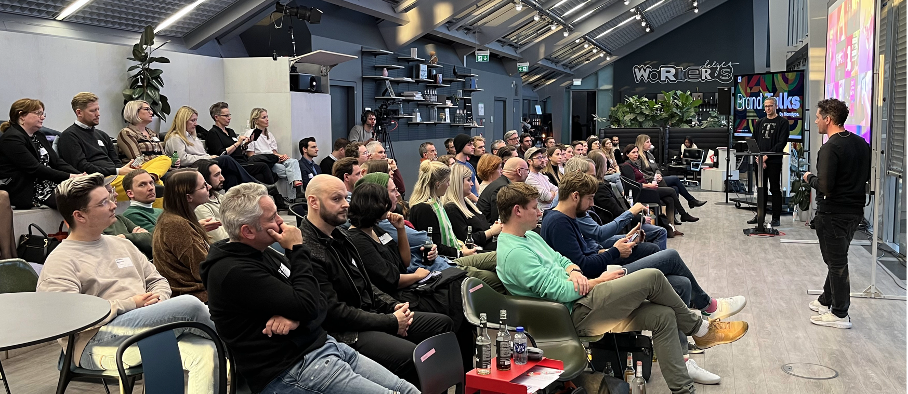
Brand Talks München verpasst?
Nach zweieinhalb Jahren Pause fanden Mitte November in München die 31. Brand Talks statt, veranstaltet von Monotype. Die wirtschaftlichen Vorzeichen haben sich in diesem Zeitraum extrem verändert. Auf den Corona-Lockdown folgten mehrere Infektionswellen, unterbrochene Lieferketten, die Energiekrise, Inflation und zuletzt Kurseinbrüche an der Börsen und bei den Kryptowährungen. Die Weltwirtschaft im Dauerkrisenmodus. Wie kommen wir da wieder raus? Rund 100 Besucher:innen bekamen Antworten auf diese Frage.
Wenn die Umsätze zurückgehen, sparen Unternehmen zuerst bei den Dingen, die sich schnell zusammenstreichen lassen: Werbung und Marketing. Genau das ist falsch, sagen die Markenprofis, denn Sparmaßnahmen in diesem Bereich sind oft der Beginn einer Abwärtsspirale. Sie betonen, dass es gerade in schlechten Zeiten von Vorteil sei, vertrauensvoll mit den Verbrauchern zu kommunizieren. Diese Ansicht vertritt auch der Brand-Talks-Eröffnungssprecher Simon Betsch, Managing Partner bei der Markenberatung KMS TEAM.
KMS versteht sich als Think-and-do-tank, der früh in Veränderungsprozesse einsteigt, damit eine Transformation nachhaltig gelingt. In seinem Vortrag belegt Betsch mit mehreren Beispielen, wie Unternehmen in einer sich ändernden Welt Orientierung schaffen. Wenn die Menschen der Politik und den Medien nicht mehr trauen, schlägt die Stunde der Marken. Insbesondere in Zeiten von sozialen und ökonomischen Umwälzungen können Unternehmen die strategische Markenführung als Motor für die Transformation nutzen und sich glaubhaft auf die neuen Erwartungen der Verbraucher einstellen.
„ “Ein Unternehmen, das seine Marke zeitgemäß steuert, stärkt vier wichtige Erfolgsfaktoren: Konsistenz, Relevanz, Differenzierung und Engagement. ” “
In der Anmoderation des nächsten Vortrags erinnerte der Brand-Talks-Gastgeber Jürgen Siebert daran, dass der Klimaschutz ins Stocken geraten sei und die junge Generation keine Geduld mehr mit der Politik habe. Umso wichtiger sei es, dass NGOs und Marken weiter kämpfen. Dies war die Brücke zum ersten lupenreinen Brand Talk, also Marke plus Agentur auf der Bühne: Karl Nowak, verantwortlich für das digitale Business beim WWF und Christian Weigel, Managing Director bei Digitas Pixelpark, stellten die Metaverse-Kampagne saveyour.world vor. „Das erste Metaverse für den guten Zweck“ so beschreibt Karl Nowak die Aktion, „auch wenn ich den Begriff ‚Metaverse‘ hasse.“
Der WWF sieht in den Methodiken, die hinter der virtuellen Welt stehen, die Chance, ein junges, engagiertes Publikum zu erreichen.
„ “Umweltschutz braucht Aufmerksamkeit und Tatkraft, dafür gehen wir neue Wege. Wir wollen das Bewusstsein für globale ökologische Krisen schärfen, zum Beispiel die Plastikflut und das Artensterben. Und dabei setzen wir auf digitale Innovation. Mit der Kampagne schlägt der WWF eine Brücke zwischen der virtuellen Welt und der realen Welt. ” “
fasst Nowak die Kampagne zusammen
Moderator Jürgen Siebert stellte in der nachfolgenden Q&A-Session die These in den Raum, dass der im Branding jahrelang gepredigte Kundenfokus ausgedient habe. Der einst von Amazon erfundene Shopping-Algorithmus ‚Wenn dir dies gefällt, gefällt dir auch das‘ habe die Kunden in eine Konsumblase gelockt.
„ Seit 10 Jahren treibt derselbe Algorithmus die Menschen in den sozialen Medien in Meinungsblasen – der Nährboden für Fake News und Verschwörungserzählungen. Das hat die einstigen Musterknaben der Demokratie tief gespalten; USA, England, Frankreich und auch Deutschland. Deshalb müssen Marken heute die Gesellschaft, und nicht den einzelnen Kunden in den Fokus nehmen. “
fordert Siebert.
Diese Einstellung werde inzwischen auch an der Börse honoriert, wo die EU stichhaltige Nachhaltigkeitsreports fordert.
Ein Beispiel für soziales Marketing ist die Telekom-Kampagne „Gemeinsam #GegenHassImNetz“, wo ein Social-Media-Flashmob die John-Farnham-Hymne „You’re the Voice“ anstimmt. Warum es für diese Art der Kommunikation einer exklusiven Hausschrift bedarf, erläuterten Hendrik Bruning, Creative Director bei MetaDesign Düsseldorf, und Andreas Kirpal, Senior Brand Manager bei der Deutsche Telekom AG im folgenden Brand Talk. Seit einem Jahr arbeitete die Telekom an der Entwicklung und Einführung ihrer neuen Markenschrift TeleNeo, ausgezeichnet vom reddot Award. Sie ersetzt Tele-Antiqua und Tele-Grotesk, die seit rund 15 Jahren im Einsatz waren.
Mit der neuen Schrift und weiteren visuellen Bausteinen bringt die Deutsche Telekom ihren Markenauftritt auf Zukunftskurs. Neben handwerklichen Verbesserungen zeichnet die neue Schrift Charakterstärke und Neutralität aus. Auch technisch ist sie auf dem aktuellen Stand, dank der Variable-Font-Technologie, die vor allem beim Einsatz in VR- und AR-Anwendungen sowie in Werbevideos wertvolle Dienste leisten kann, wenn es um Lesbarkeit und Animation geht.
Den Schlusspunkt bei den Münchener Brand Talks setzte Monotypes Senior Type Director Phil Garnham aus London. Er präsentierte die Ergebnisse einer wissenschaftlichen Studie, die sich der emotionalen Wirkung von Schrift im Branding widmet. Es ist die erste neutrale Untersuchung, die den Einfluss von Schrift auf das Erlebnis, die Assoziationen und die emotionale Reaktion gegenüber Marken und deren Botschaften qualitativ und quantitativ belegt. Hierzu hat Monotype in Zusammenarbeit mit Neurons, eine Forschungseinrichtung für angewandte Neurowissenschaften, drei Schriften unterschiedlicher Genres unter die Lupe genommen. Dabei kam heraus, dass allein deren Aussehen einen starken Einfluss auf die Emotionen der Leserschaft hat, wobei sich positive Reaktion um bis zu 13 % steigern lassen; üblich sind um die 5 %.
Abschließend gab Jürgen Siebert den Besuchern noch zwei wertvolle Tipps auf den Weg zum anschließenden Buffet: Erstens: Sie können die Studie kostenlos downloaden; und zweitens liefert Sie Ihnen genau die Zahlen, die Sie brauchen, um Ihrer Finanzabteilung ein ordentliches Marketingbudget aus dem Kreuz zu leiern.